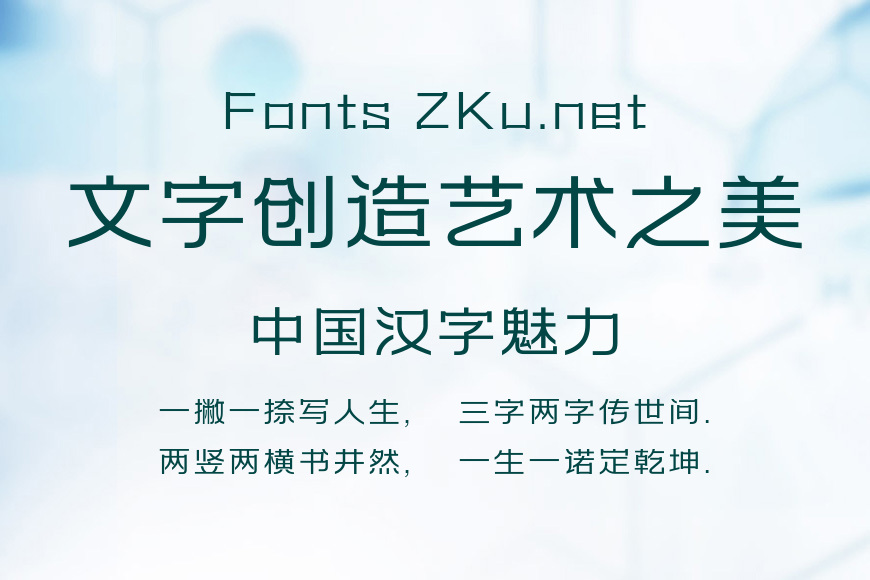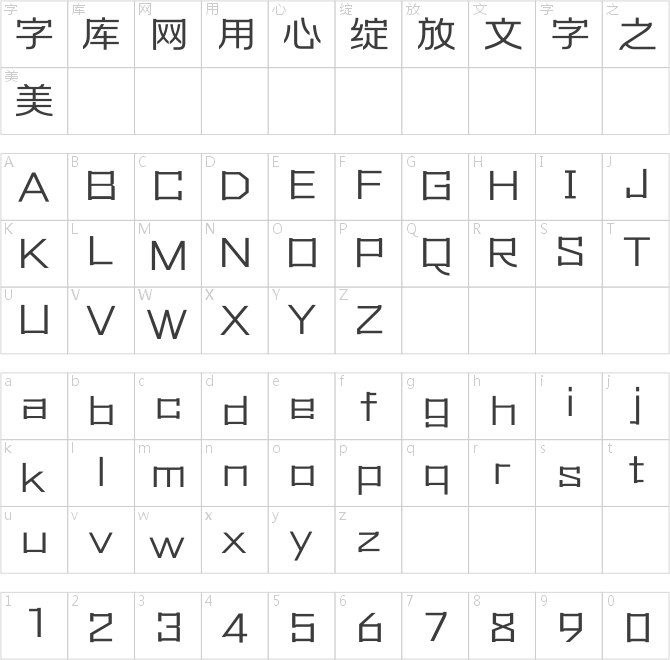
方正创黑 详情页
字体名称: 方正创黑
方正创黑
方正创黑介绍
这款字的创意风格来源于我们最常用的黑体字,在黑体的基础上增强了字体结构的饱满度,加强了笔画的韵律和节奏感,以及规范度让整体字形更加简洁易记同时兼备艺术感。在横竖笔画转角的处理上,加以传统书法的提笔落笔,让整体字形彰显力量感顿挫感,在撇捺笔画的走势上,借鉴了宋体字笔画的柔和度,让整体字形摒弃黑体字的生硬,让它更具优雅性, 在创作过程中,我们始终让字形兼具力量与优雅并存,从而在简洁的字形中,形成自身最大的特征。适用于产品包装、海报视频、大标题及周边等领域。